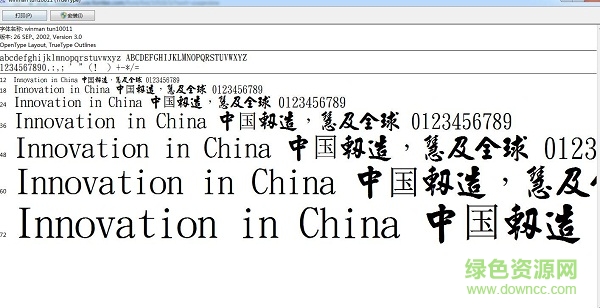
金梅毛行書(shū)國(guó)際碼(winman tun10011)是一款漂亮的行書(shū)字體,線(xiàn)若游絲,流暢大氣,藝術(shù)性高,適用于影視海報(bào)設(shè)計(jì)、書(shū)籍封面等領(lǐng)域,喜歡的朋友快來(lái)綠色資源網(wǎng)下載吧!
行書(shū)是楷書(shū)的快寫(xiě),相傳始于漢末。它不及楷書(shū)的工整,也沒(méi)有草書(shū)的草率。每個(gè)字呈現(xiàn)大小不同,存在著一個(gè)字的筆與筆相連,字與字之間的連帶,既有實(shí)連,也有意連,有斷有連,顧盼呼應(yīng)。